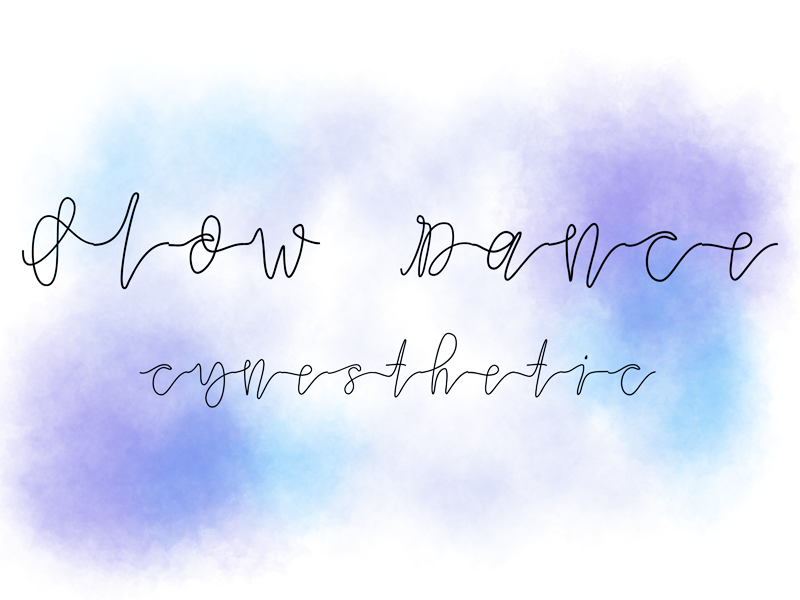
Slow Dance Font – Fonte Grátis
Slow Dance Font
A fonte ‘Slow Dance Font’ é uma opção ideal para quem busca uma escrita elegante e fluida que transmite tranquilidade. Desenvolvida pelo designer Cynesthetic, esta família de caracteres manuscritos se destaca pela sua fluidez natural e conexão entre as letras. A descrição original explica perfeitamente o objetivo deste projeto: criar uma ligação suave mas perceptível entre os diferentes elementos do texto, garantindo que não haja um salto brusco na leitura que possa desestabilizar o fluxo visual. O resultado é uma fonte que parece ter sido criada à mão, onde cada letra se tornou uma versão escrita de algo tão delicado e suave quanto a dança. Não importa a tonalidade escolhida, seja negrito, itálico ou normal, ‘Slow Dance Font’ oferece um toque de calma e tranquilidade que pode tornar o processo de escrita mais leve e relaxante para qualquer designer. Se você está procurando por uma fonte que não apenas se destaca em sua página web ou material impresso, mas também transmite a sensação de ser confortável para ler, ‘Slow Dance Font’ é definitivamente um investimento inteligente.